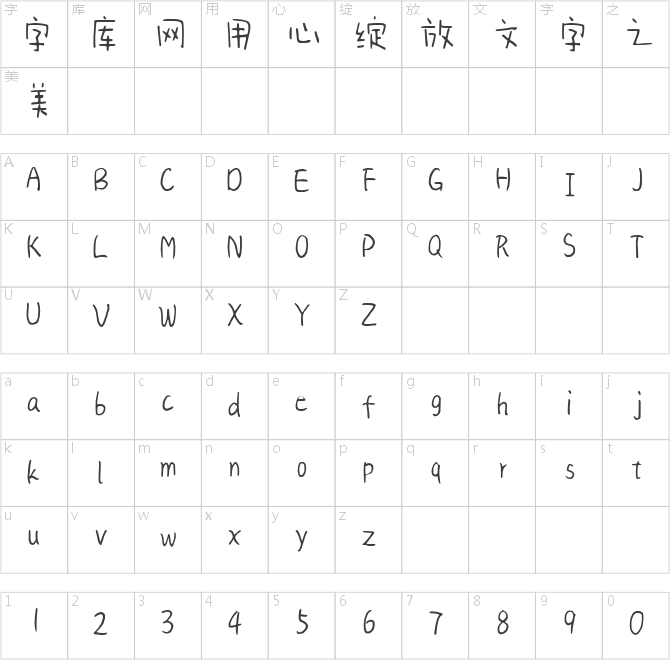
孤單就像連鎖反應(yīng)字體gudanjiuxiangliansuofanying字庫是一款讓人賞心悅目、百看不厭的中文字體,適合各類廣告和產(chǎn)品包裝設(shè)計(jì)應(yīng)用,字體大小8.9MB,格式為ttf字體,上傳用戶是細(xì)雪無聲,作者/版權(quán)方為字語字庫